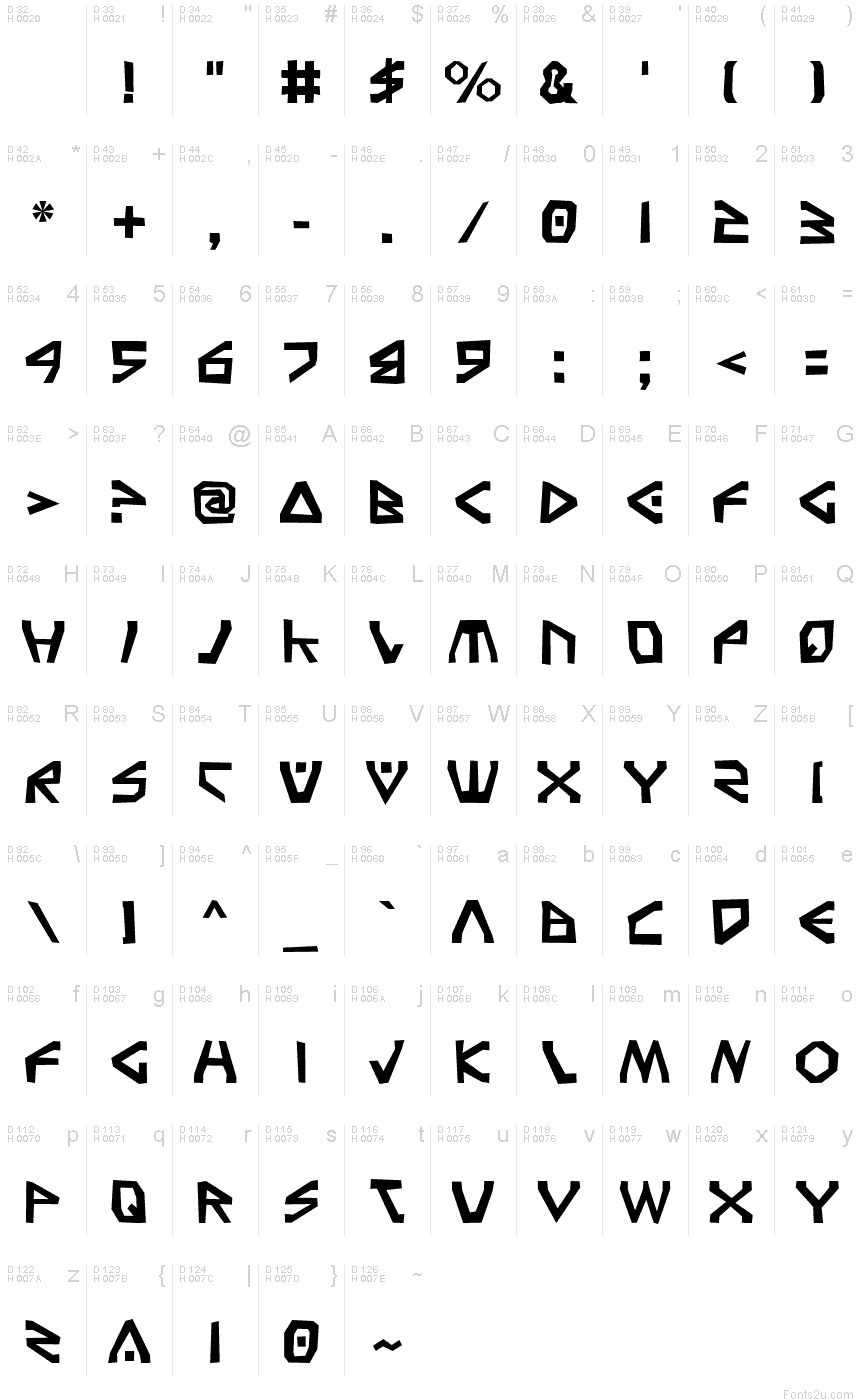
Terra Firma Rough von Iconian Fonts ist eine kostenlose, kantige Techno-Schriftart mit einem harten Sci-Fi-Charakter. Die Buchstaben wirken wie aus breiten, geometrischen Keilen gemeißelt – mit schrägen Schnitten, dreieckigen Verbindungen und blockartigen Formen, die dem Design einen architektonischen statt glatten Look verleihen.
Sie passt perfekt zu Gaming-Logos, Flyern für elektronische Musik, Plakatüberschriften, Titelkarten sowie Cover-Texten für Comics oder Sci-Fi, bei denen die Worte stabil und gepanzert wirken sollen. Als kostenlose Schrift eignet sie sich besonders gut für kurze Display-Anwendungen und Monogramme, da die aggressiven Diagonalen und abgeschnittenen Ecken selbst wenigen Buchstaben eine kraftvolle, wie konstruiert wirkende Präsenz verleihen.